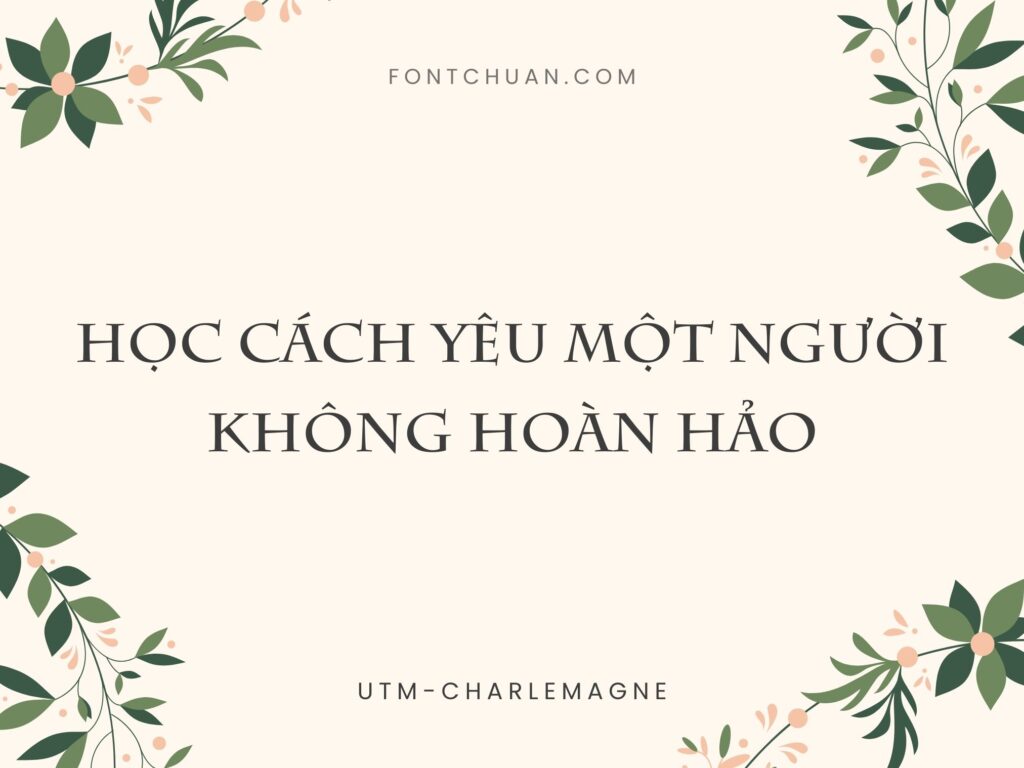
Font UTM Charlemagne Việt Hóa
UTM Charlemagne là phiên bản Việt hóa của font chữ Charlemagne, một kiểu Font Serif mang phong cách cổ điển, được thiết kế bởi Carol Twombly và phát hành bởi Adobe. Font này nổi bật với các ký tự in hoa có đường nét tinh tế, gợi nhớ đến phong cách chữ khắc trên đá thời La Mã cổ đại. Phiên bản Việt hóa đã được thực hiện bởi Công ty TNHH Vitoen, hỗ trợ đầy đủ tiếng Việt cùng hơn 100 ngôn ngữ khác. Đây là một trong những font được cộng đồng thiết kế sưu tầm và chọn lọc nhằm đáp ứng nhu cầu đa dạng trong thiết kế.
UTM Charlemagne có cấu trúc chữ với các nét thanh mảnh và chi tiết tinh xảo, tạo nên sự sang trọng và uy nghiêm. Font này phù hợp cho các ứng dụng như thiết kế tiêu đề, logo, biển hiệu và các ấn phẩm in ấn yêu cầu sự trang trọng và cổ điển. Các ngành nghề như quảng cáo, giáo dục, công nghệ và bất động sản có thể tận dụng UTM Charlemagne để tạo điểm nhấn độc đáo trong thiết kế.